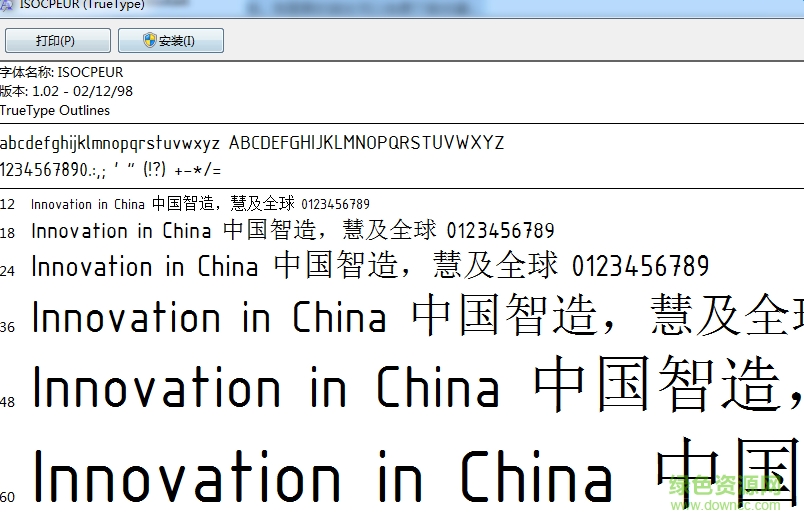
isocpeur字體是一款英文字體庫中的個(gè)性字體,該字體可以廣泛應(yīng)用于美術(shù)設(shè)計(jì)、廣告設(shè)計(jì)、ppt、影視制作以及任何使用文字的領(lǐng)域,有需要的朋友可以免費(fèi)下載收藏。
isocpeur字體是一款極具個(gè)性的英文字體,該字體的字型非常大氣,有喜歡的朋友可以來綠色資源網(wǎng)下載使用!